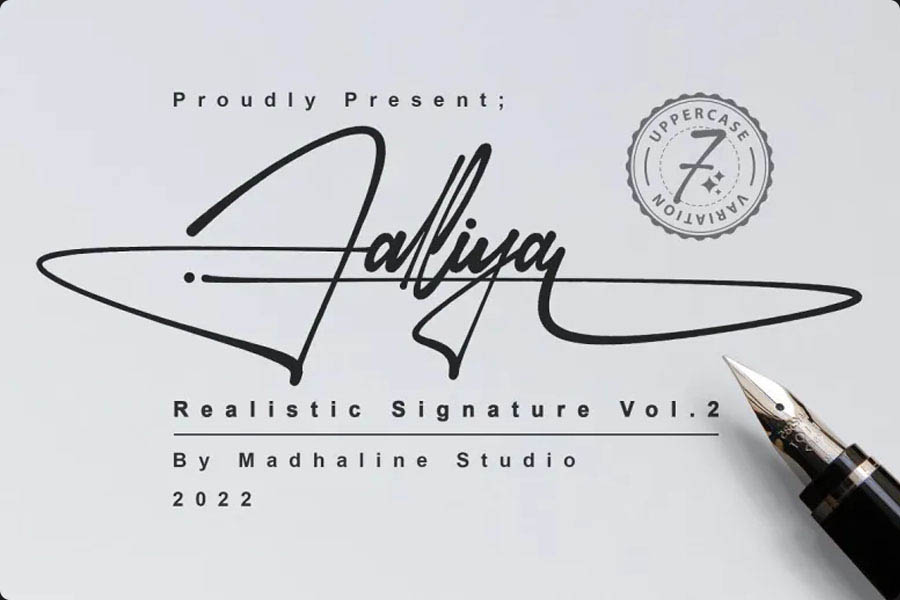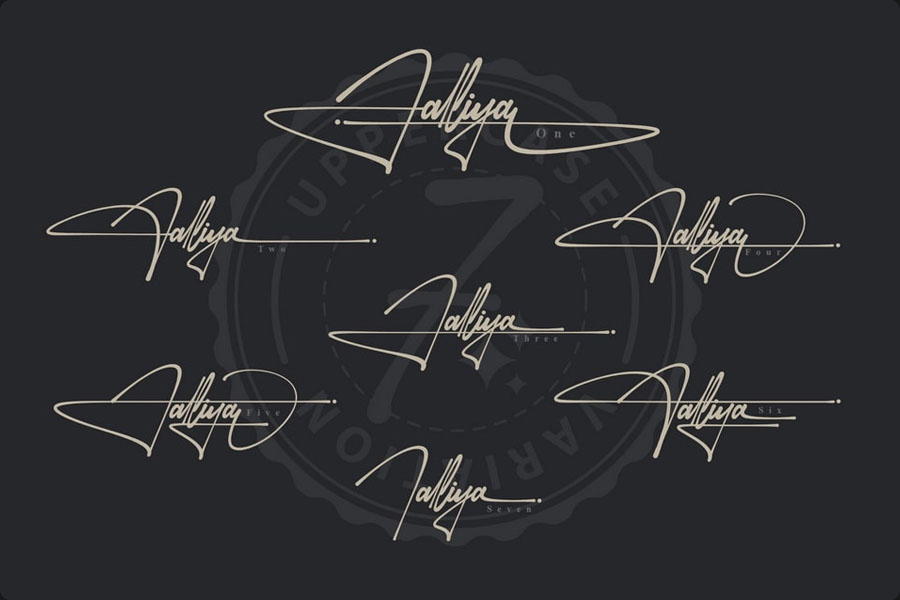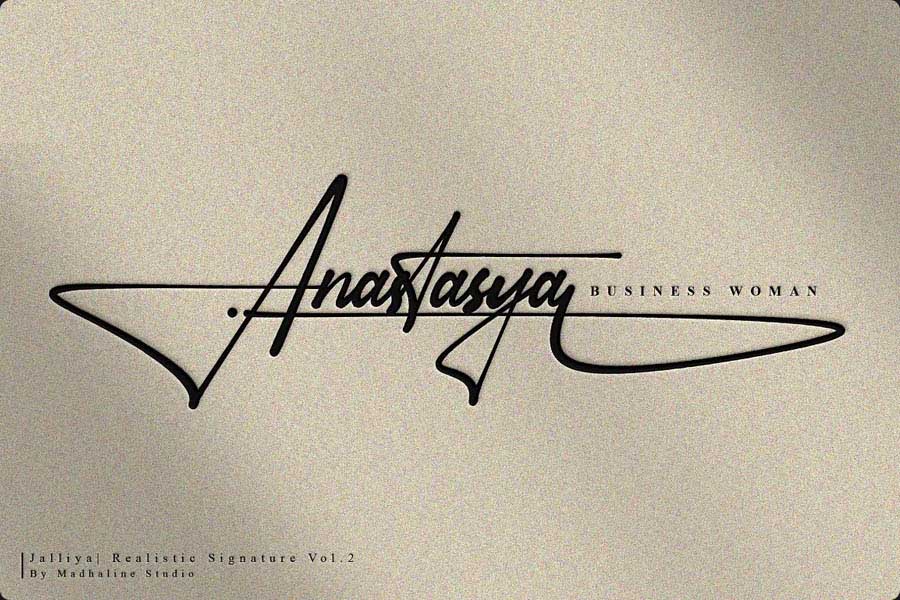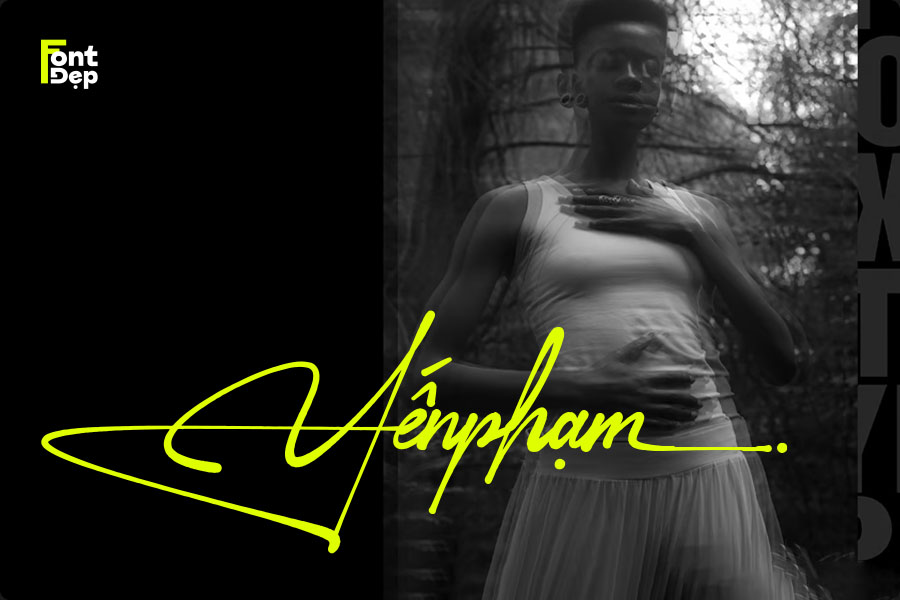
Full 7 kiểu font chữ ký mềm mại viết tay TH Jalliya Việt Hoá
Nếu bạn đang tìm một bộ font chữ ký mang đậm tính cá nhân, mềm mại như viết tay thật, lại có nhiều phong cách để tùy biến – thì Jalliya 7 Realistic Signature Vol.2 chính là lựa chọn hoàn hảo. Đây là bộ font chữ được thiết kế bởi Madhaline Studio, bao gồm 7 kiểu chữ ký khác nhau cùng 2 kiểu đuôi trang trí, tất cả đều mang vẻ đẹp tinh tế, tự nhiên và đậm chất thủ công.
Jalliya – Font chữ ký cao cấp với 7 biến thể hoàn chỉnh
Điểm nổi bật của bộ font Jalliya là mỗi kiểu chữ đều mang sắc thái riêng, từ nhẹ nhàng thanh lịch đến đậm nét sang trọng, giúp bạn thoải mái lựa chọn theo phong cách thiết kế:
• Jalliya One: Nét mảnh, nhẹ và mềm – phù hợp cho những thiết kế tinh tế như bìa sách, lời mời, trích dẫn nghệ thuật.
• Jalliya Two: Có độ nghiêng tự nhiên, gợi cảm giác viết tay thật – lý tưởng cho logo thương hiệu hoặc bao bì thủ công.
• Jalliya Three: Các nét uốn lượn mềm mại, đầy chất thơ – phù hợp với thiệp cưới, thư cảm ơn hoặc sản phẩm handmade.
• Jalliya Four: Dày và nổi bật, tạo điểm nhấn mạnh – thích hợp dùng làm tiêu đề hoặc nhận diện thương hiệu cá nhân.
• Jalliya Five–Seven: Biến thể có kết nối chữ liền mạch, cân đối hoặc trang trí – giúp tạo bố cục chữ ký đẹp mắt, không nhàm chán.
Bên cạnh đó, bộ font còn đi kèm 2 kiểu đuôi chữ Tail (Jalliya Tail 1 & Tail 2), giúp bạn dễ dàng thêm các nét nối cuối chữ cái để tăng độ tinh xảo và thẩm mỹ trong từng con chữ.
Font Jalliya đã được Việt hóa trọn bộ, hỗ trợ đầy đủ các dấu tiếng Việt như sắc, huyền, hỏi, ngã, nặng... giúp bạn yên tâm sử dụng trong các thiết kế cá nhân hóa, in ấn chuyên nghiệp mà không gặp lỗi thiếu ký tự. Font tương thích tốt trên mọi phần mềm phổ biến như Canva, Photoshop, Illustrator, kể cả dùng online hay offline.